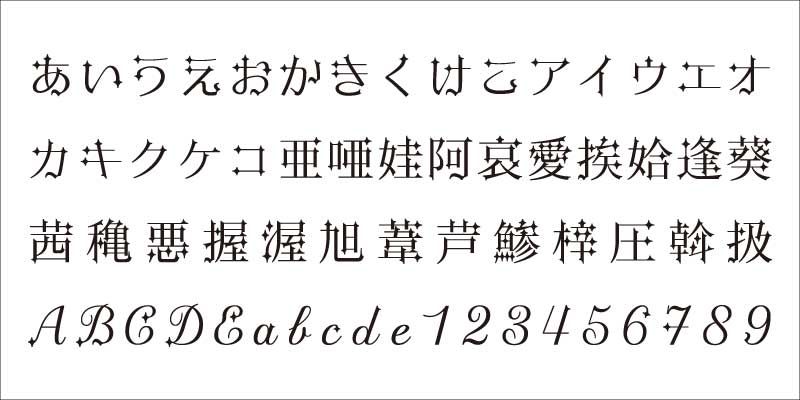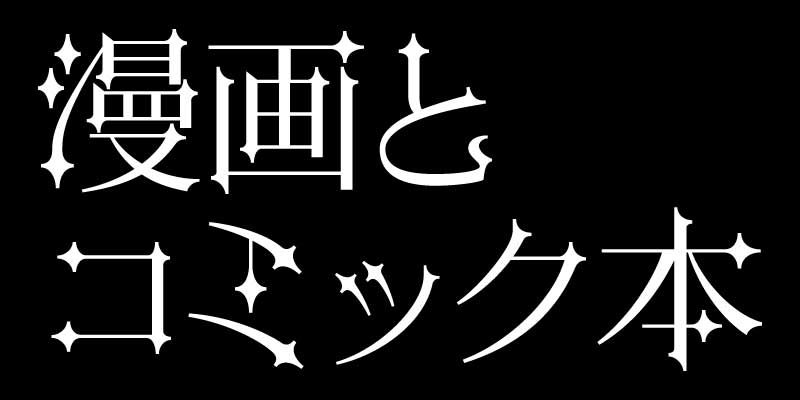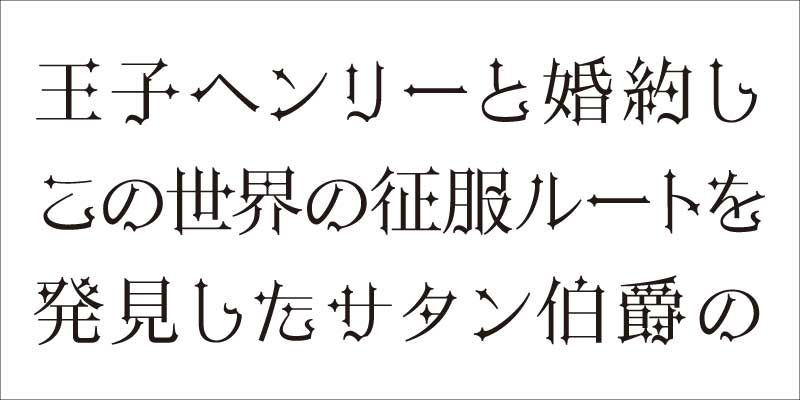
Das Designkonzept dieser Schrift ist es, „eine originelle Schrift mit der zurückhaltenden Qualität des traditionellen Mincho-Stils zu schaffen.“ Jeder Schriftzug hat einen scharfen Anfangspunkt wie der eines Hechts und einen sanft geschwungenen Harai-Abschluss wie ein langes, gebogenes Band.